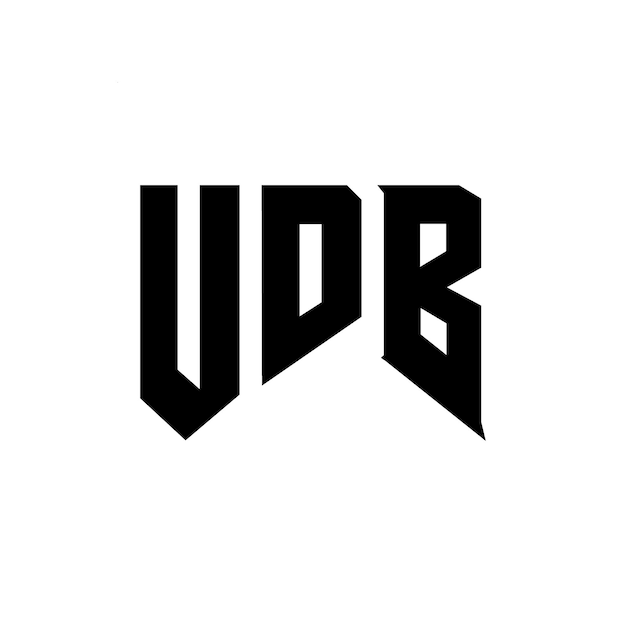
Design de logo de lettre VDB pour une entreprise de technologie VDB logo design combinaison de couleurs noir et blanc VDB logo VDB vecteur VDB design VDB icône VDB alphabet VDB typographie logo design